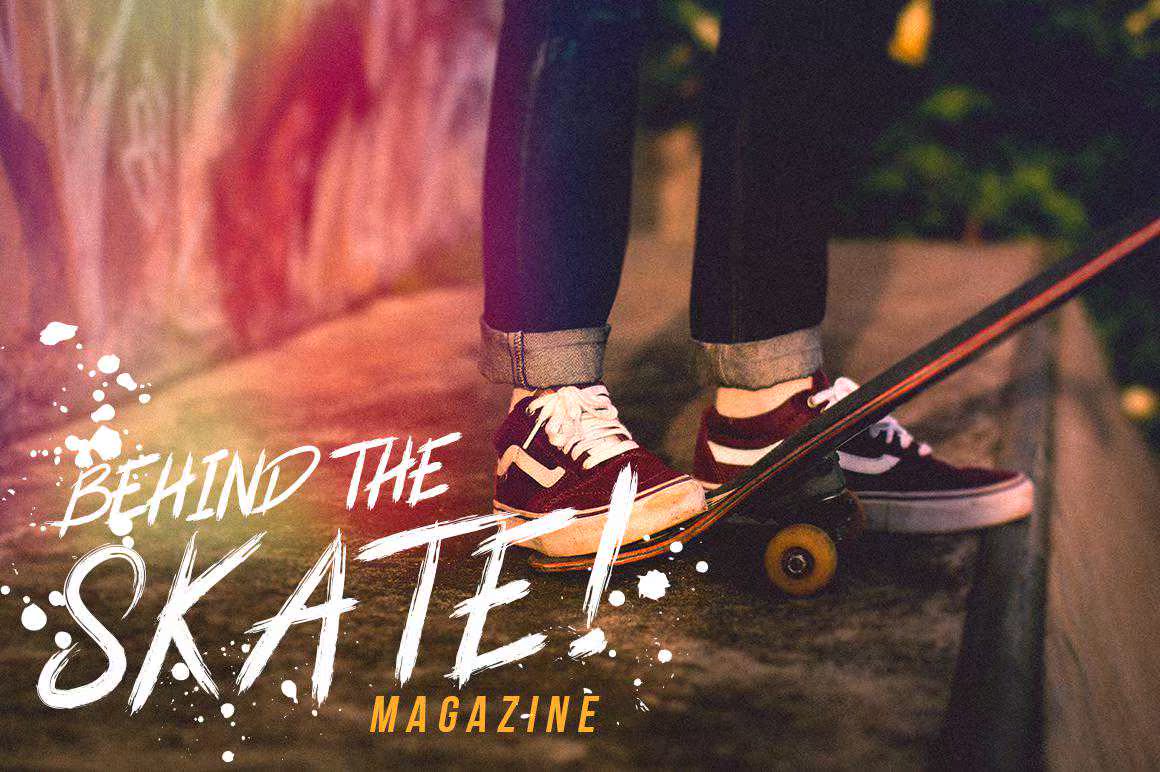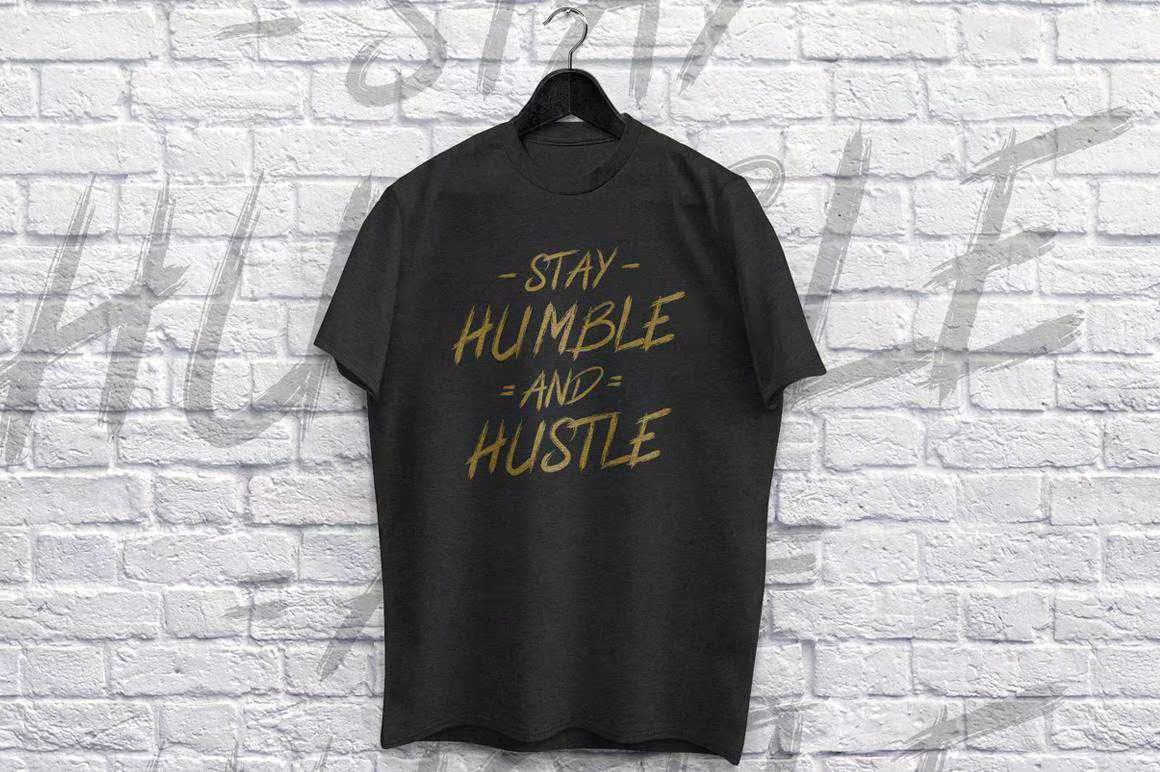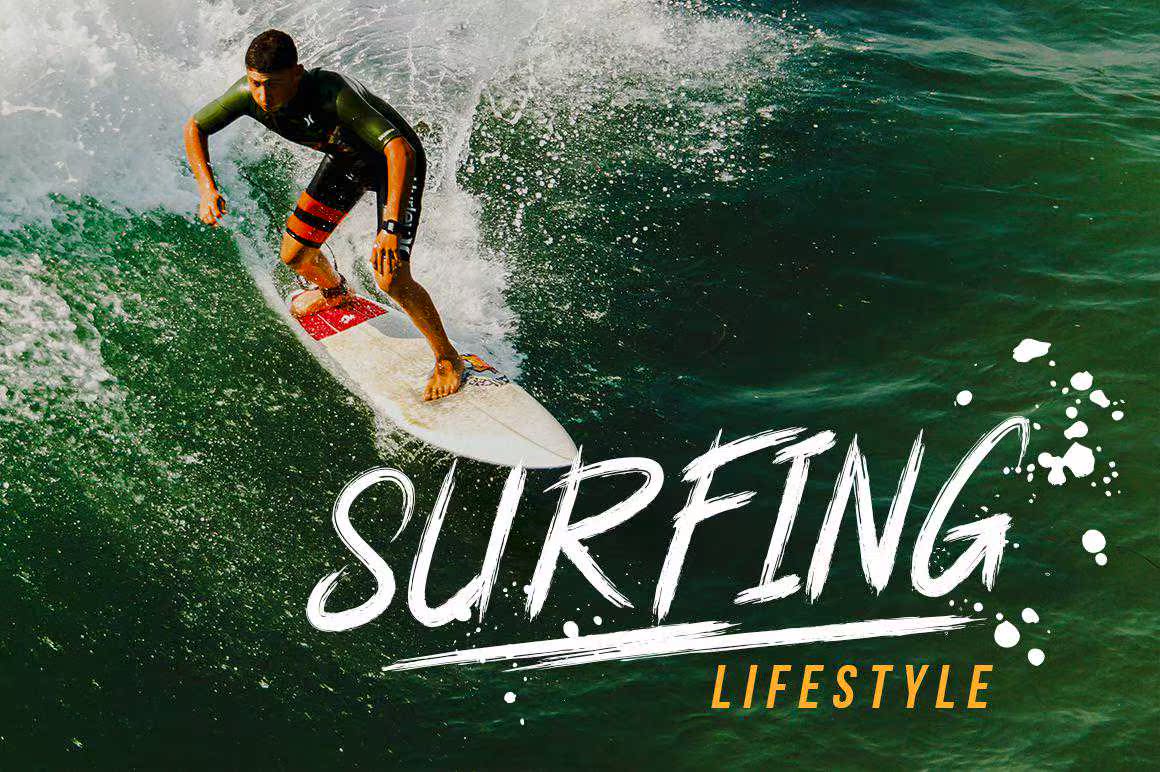
GraniteisHandleDeAuthenticationFontBrush具有TylishStreetLifeStyle和LooksLekeExtremeSportStyleUsage。最佳匹配徽标、标题、标题、印花、服装和其他创造性加工可能性。GraniteisHandleDeAuthenticationFontBrush具有TylishStreetLifeStyle和LooksLekeExtremeSportStyleUsage。最佳匹配徽标、标题、标题、印花,服装和其他创意加工的可能性。